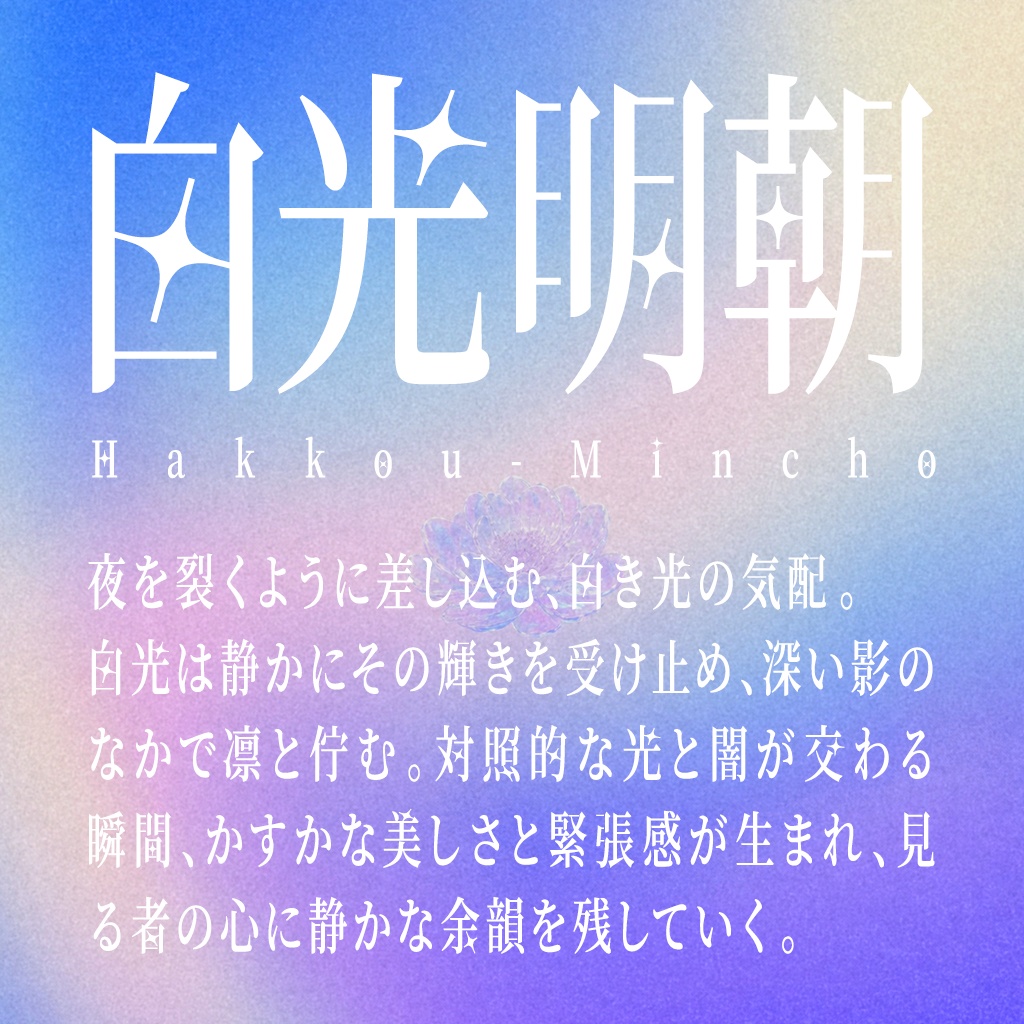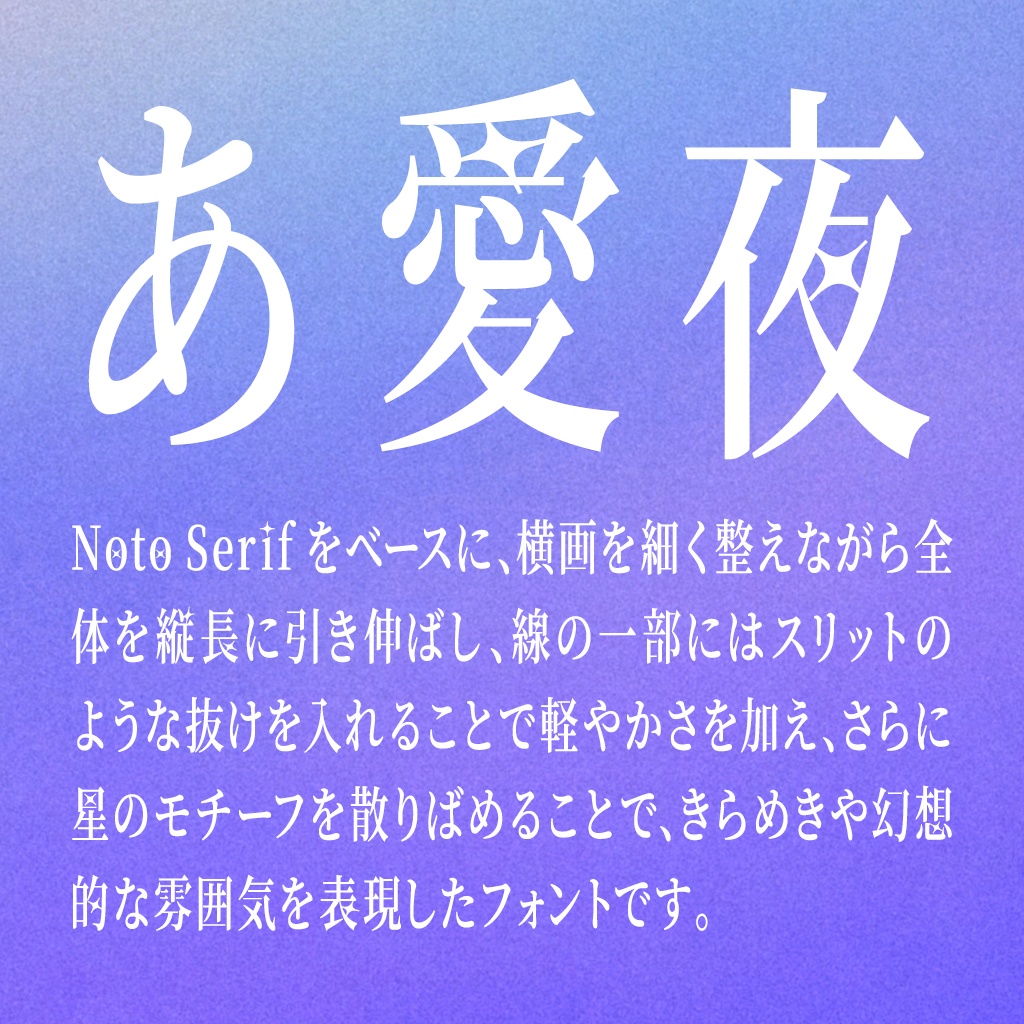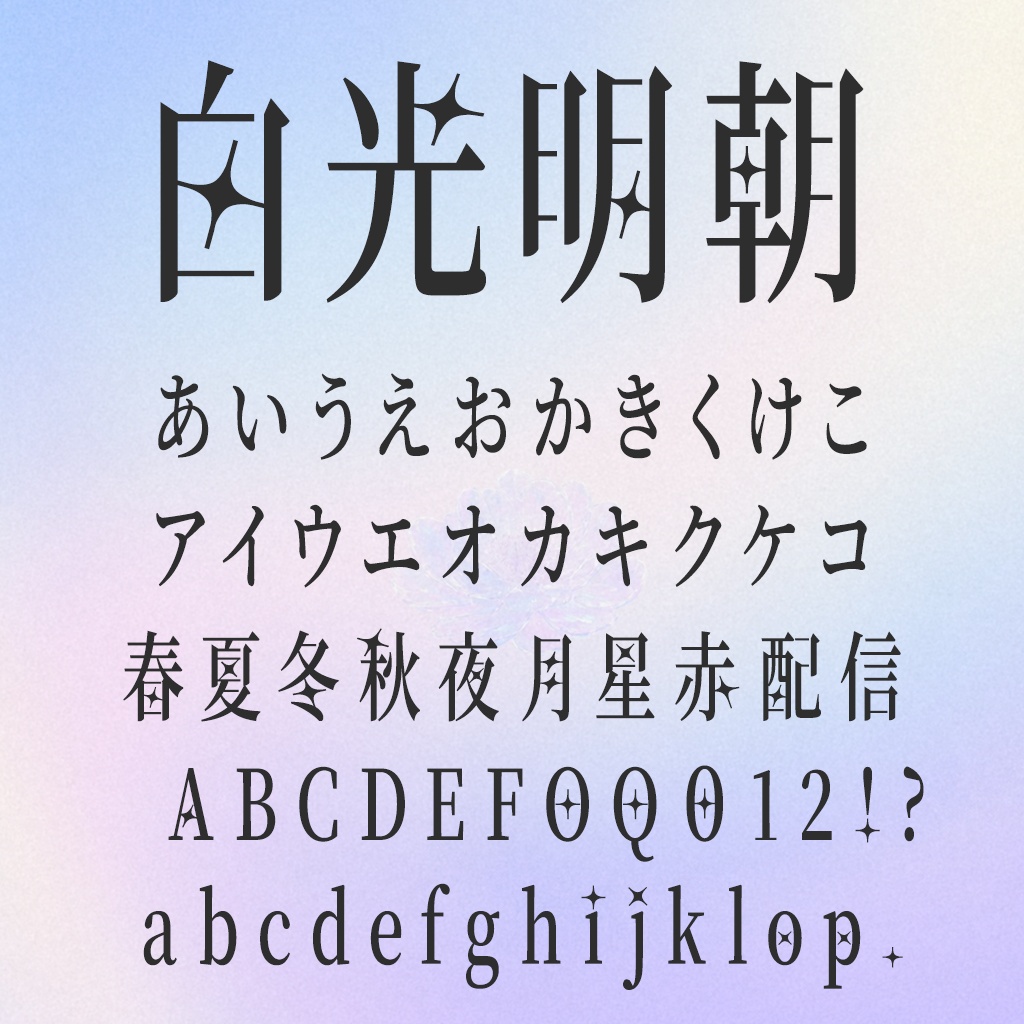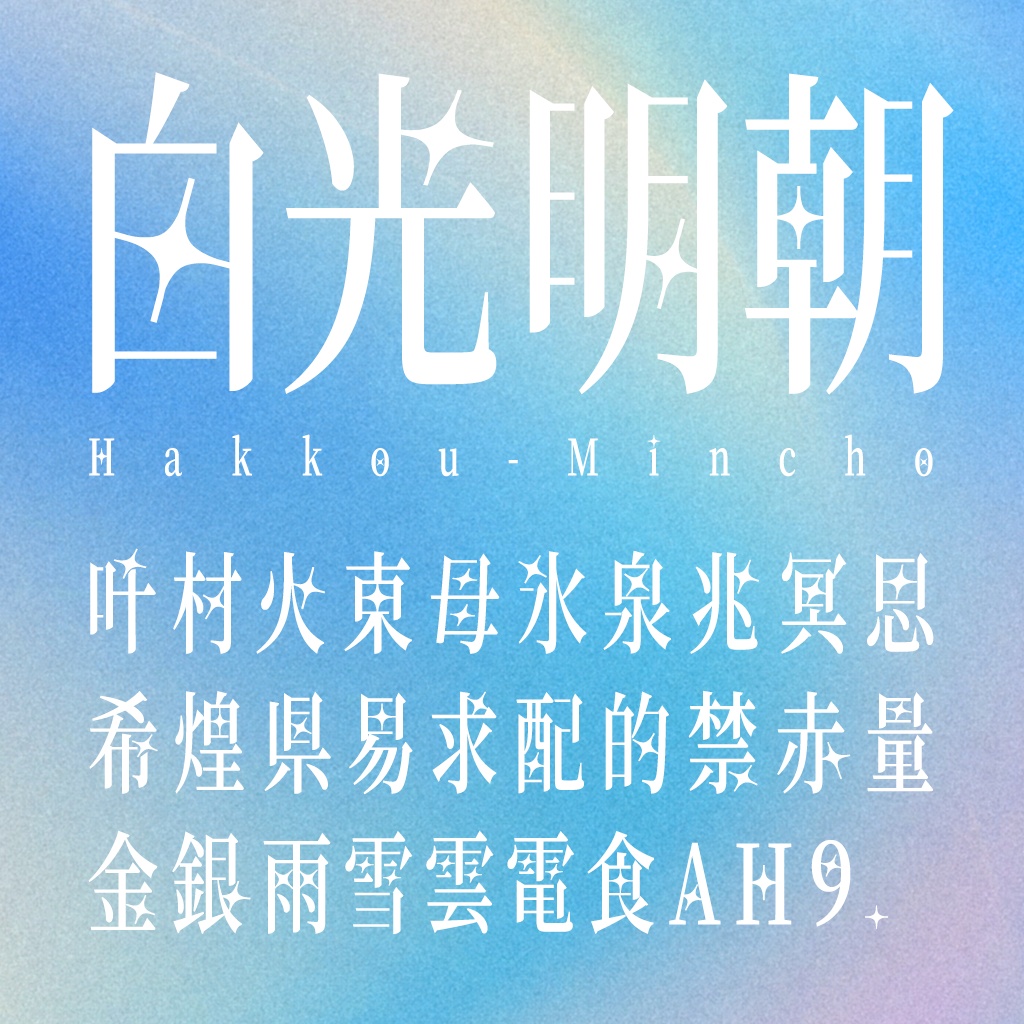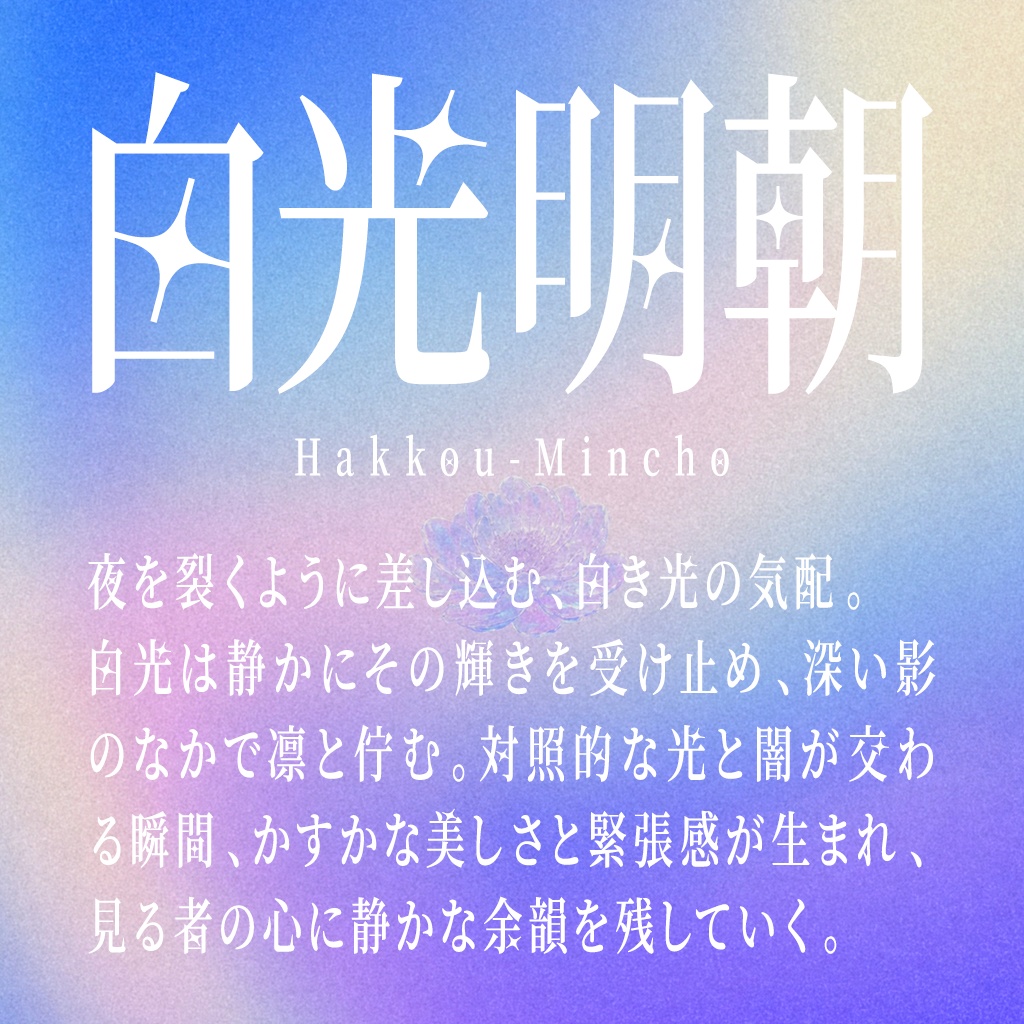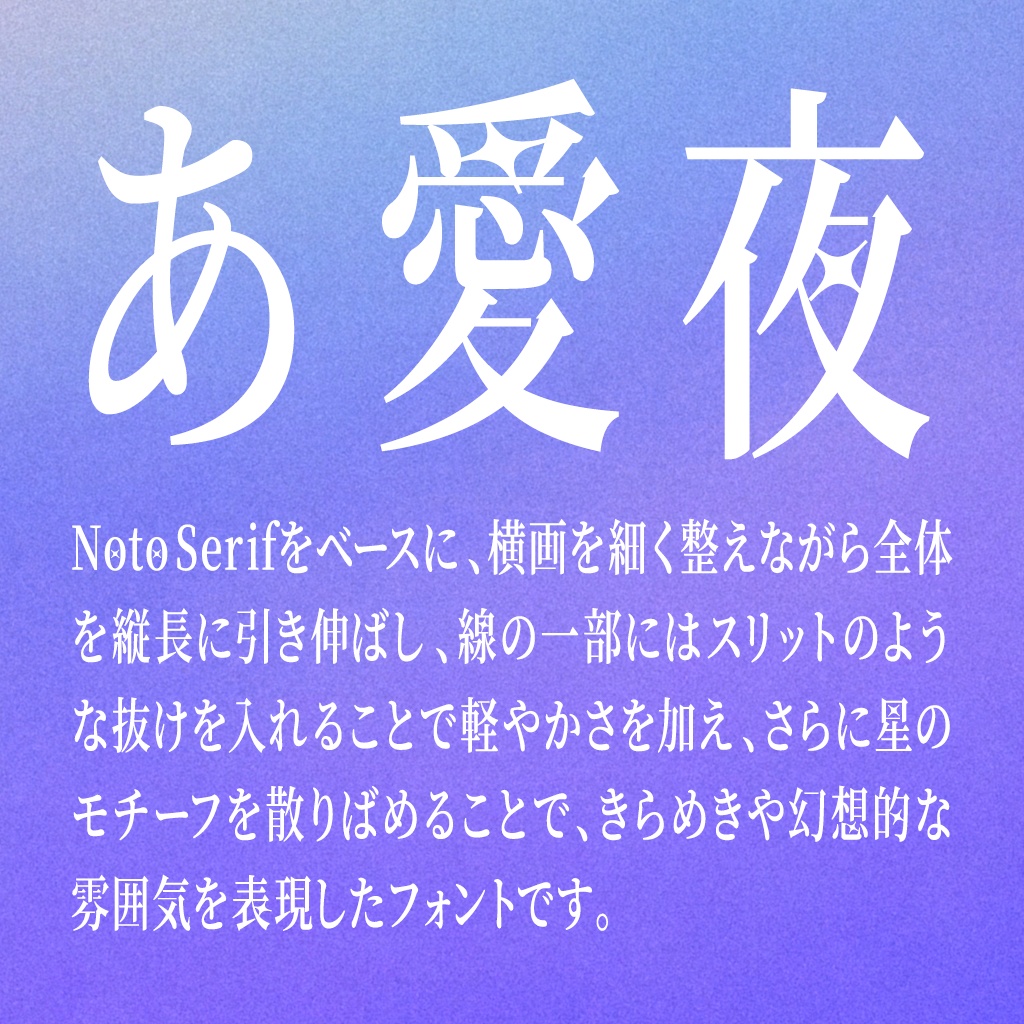
白光明朝(フリーフォント)
【概要】 白光明朝は、Noto Serifを改変したフリーフォントです。 横画を細く整えながら全体を縦長に引き伸ばし、線の一部にはスリットのような抜けを入れることで軽やかさを感じられるフォントとなっています。 さらに、文字には星のモチーフを散りばめて、きらめきや幻想的な雰囲気を表現しています。(ランダムで一部の文字のみに適用しています) 無料版と投げ銭版(¥500)のフォント内容は同一です。 【ライセンス・規約について】 このフォントはSIL Open Font License 1.1で公開されています。 個人・商用にかかわらず無償で使用可能で、動画・サムネイル・ゲーム等への組み込みなどご自由にご利用ください。 詳しいSILライセンスについてはサイトをご確認ください。 https://licenses.opensource.jp/OFL-1.1/OFL-1.1.html 当フォントを利用して発生した、いかなる損害についても作者は責任を負いません。 フォントデータをダウンロードした時点で利用規約に同意したものとみなします。 【改変元フォント】 源ノゴシック/源ノ明朝/Noto Sans/Noto Serif 関係者に深くお礼申し上げます。 【アップデート】 2026/05/07《ver1.002》一部文字の崩れを調整しました。星入り文字を追加しました。 2026/05/20《ver1.003》一部文字のディティールを調整しました。星入り文字を追加しました。 2026/06/18《ver1.004》縦書き文字の一部崩れがありましたので、修正しました。星入り文字を追加しました。 ========= 星を入れたい文字などのリクエストがありましたら、今後適宜アップデートしていく予定です。 XやBOOTHのメッセージなどから、お気軽にリクエストいただけますと嬉しいです。